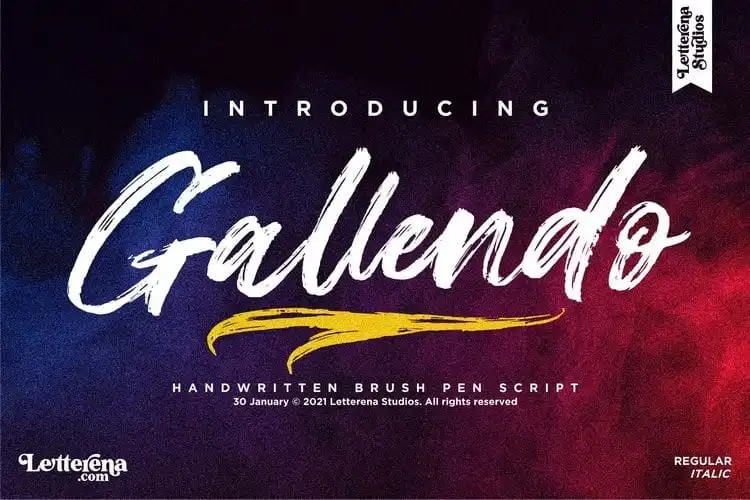
Gallendo Brush Font – Download Grátis
Gallendo Brush Font é uma fonte de estilo brush casual criada pelo Letterena Studios usando a técnica de escrever com um pincel seco. Esta elegante fonte calligráfica pode ser usada em uma variedade de projetos, desde logotipos e embalagens até cartões de convite e capas de livros. Suave e sofisticado, ela oferece um toque moderno e único que combina com os mais variados estilos de design. Seja para marcar sua marca ou criar um design exclusivo, Gallendo Brush Font está aqui para fornecer o toque perfeito em seus projetos de luxo. Com sua presença suave e versátil, você pode adicionar o toque final a qualquer projeto que precise de uma sensação única de brush. Não importa qual tópico seu trabalho aborda, Gallendo Brush Font é um recurso indispensável para designers que desejam dar vida à suas ideias.